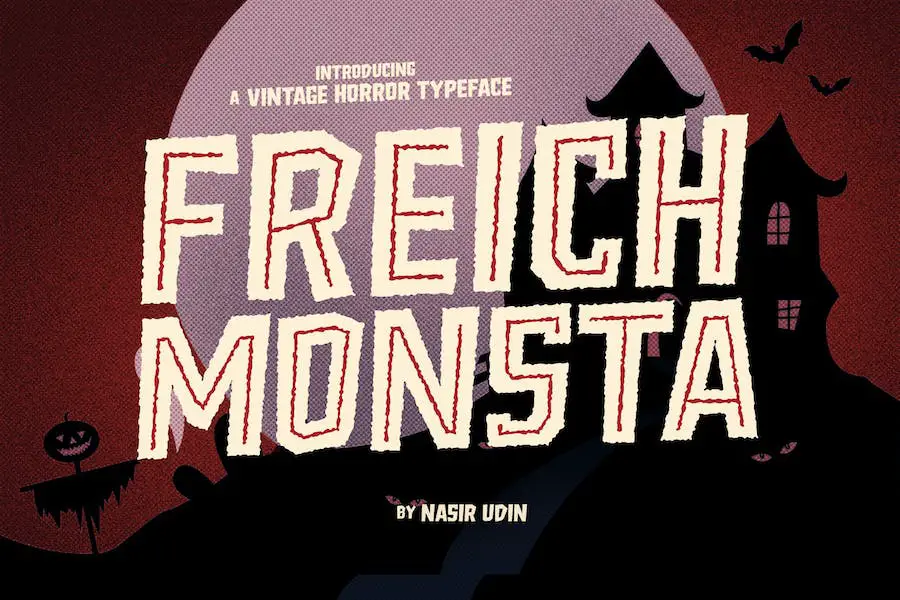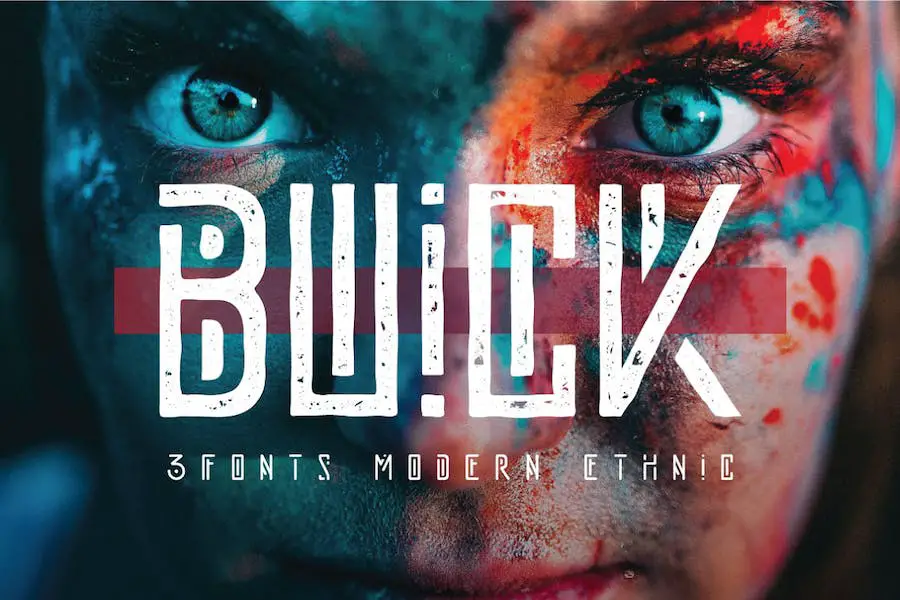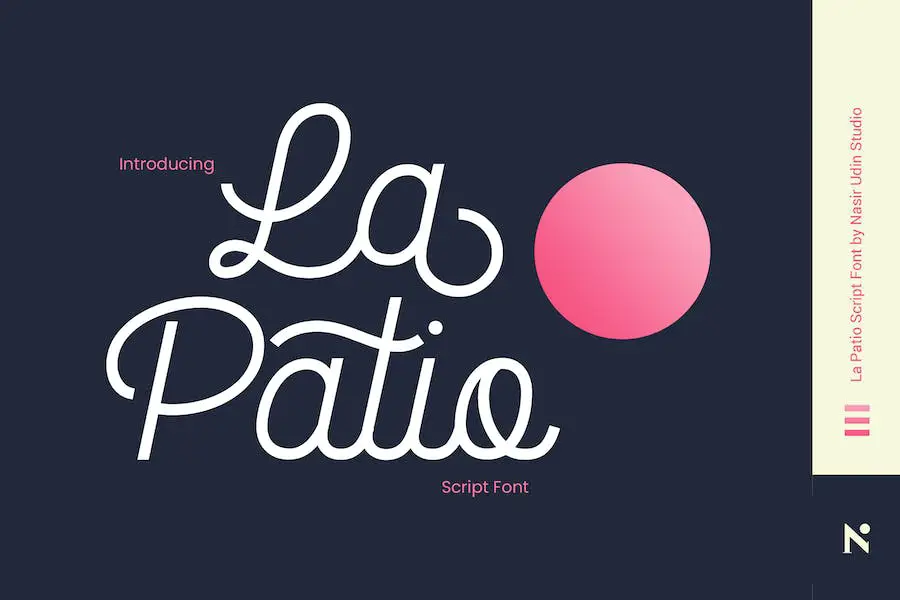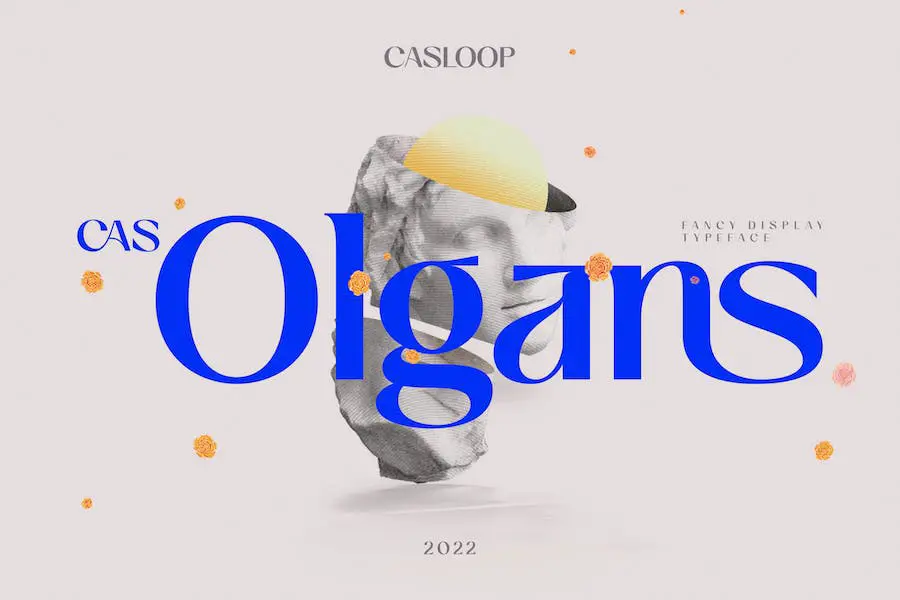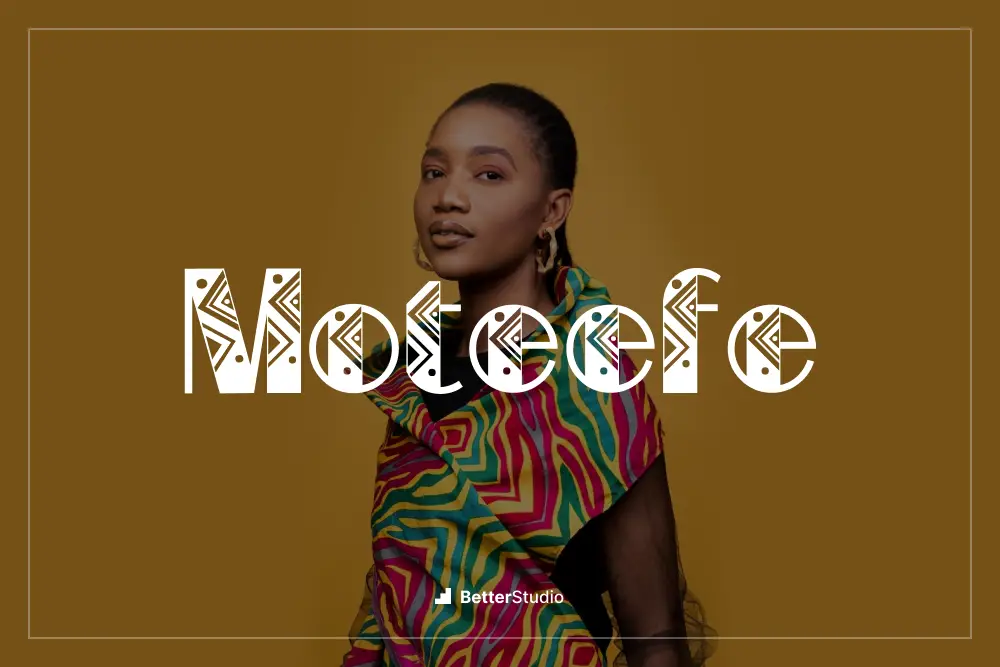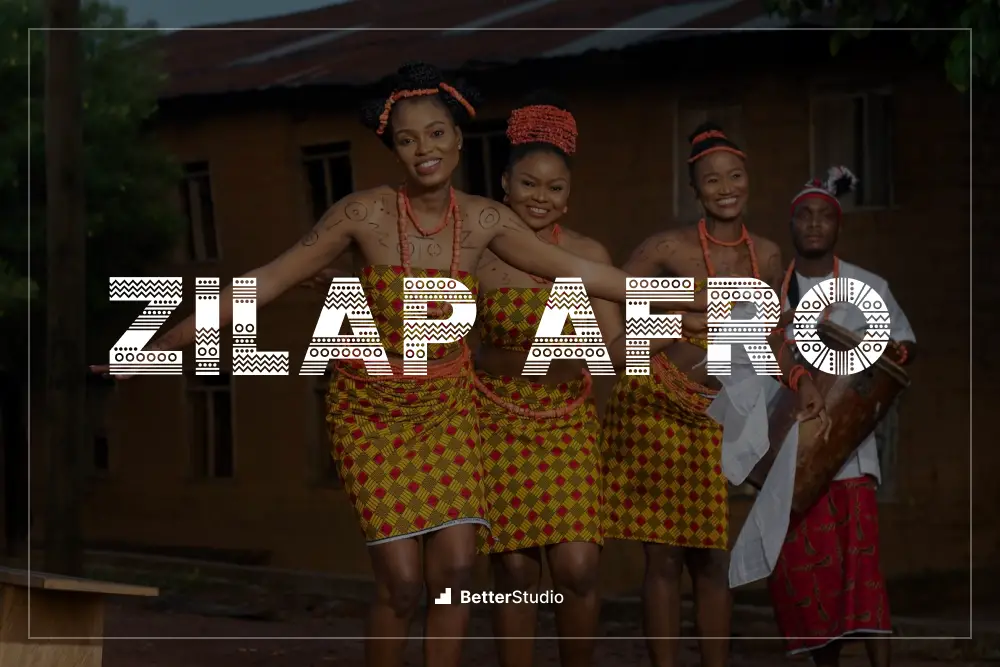
15 แบบอักษรแอฟริกันที่ดีที่สุด 2023 (ฟรีและพรีเมียม)
ในบล็อกโพสต์นี้ เราจะมาสำรวจแบบอักษรแอฟริกันที่ดีที่สุด 15 แบบที่จะนำสัมผัสแห่งวัฒนธรรมและความคิดสร้างสรรค์มาสู่การออกแบบของคุณอย่างแน่นอน แต่ก่อนที่เราจะเจาะลึก คุณอาจสงสัยว่าทำไมถึงใช้ฟอนต์แอฟริกัน?
แบบอักษรแอฟริกันนำเสนอสุนทรียศาสตร์ที่หลากหลายและหลากหลาย โดยได้รับแรงบันดาลใจจากวัฒนธรรมที่มีชีวิตชีวาของทวีป รูปแบบที่สลับซับซ้อน และสัญลักษณ์ตัวหนา แบบอักษรแต่ละแบบมีเรื่องราวของตัวเอง ช่วยให้คุณเพิ่มเอกลักษณ์เฉพาะตัวให้กับโครงการออกแบบของคุณได้
ตอนนี้เราได้ทำให้คุณสนใจแล้ว เรามาดูรายละเอียดสำคัญกันดีกว่า ในบทความนี้ เราจะนำเสนอแบบอักษรแอฟริกัน 15 อันดับแรกที่มีทั้งรูปลักษณ์โดดเด่นและใช้งานได้ดี
ตั้งแต่การประดิษฐ์ตัวอักษรที่หรูหราไปจนถึงการออกแบบที่ได้รับแรงบันดาลใจจากชนเผ่า แบบอักษรเหล่านี้ได้รับการคัดเลือกมาอย่างพิถีพิถันเพื่อให้เหมาะกับความต้องการในการออกแบบที่หลากหลาย ไม่ว่าคุณจะทำงานในโครงการสร้างแบรนด์ โปสเตอร์ หรือแม้แต่ส่วนหัวของบล็อก แบบอักษรเหล่านี้จะช่วยยกระดับงานของคุณและสร้างความโดดเด่นอย่างแน่นอน
ดังนั้น เพื่อไม่ให้เป็นการเสียเวลา กระโดดเข้าสู่โลกของแบบอักษรแอฟริกันและค้นพบอัญมณีที่ซ่อนอยู่ที่รออยู่ เตรียมพร้อมที่จะรับแรงบันดาลใจและปลดปล่อยความคิดสร้างสรรค์ของคุณในขณะที่เราสำรวจแบบอักษรแอฟริกันที่ดีที่สุด 15 แบบสำหรับนักออกแบบกราฟิก
คอยติดตามส่วนต่อๆ ไป ซึ่งเราจะเจาะลึกแต่ละฟอนต์ เน้นคุณลักษณะเฉพาะของฟอนต์ และยกตัวอย่างว่าสามารถนำมาใช้อย่างมีประสิทธิภาพในโครงการออกแบบต่างๆ ได้อย่างไร มาดำน้ำกันเถอะ!
แบบอักษรแอฟริกันระดับพรีเมียมที่ดีที่สุด
กำลังมองหาการเพิ่มกลิ่นอายแบบแอฟริกันให้กับงานออกแบบของคุณหรือไม่? การเลือกแบบอักษรแอฟริกันระดับพรีเมียมที่ดีที่สุดที่คัดสรรมาอย่างดีของเรา จะทำให้โครงการของคุณมีสุนทรียศาสตร์ที่มีเอกลักษณ์และเปี่ยมไปด้วยวัฒนธรรม อย่าพลาดแบบอักษรที่น่าดึงดูดเหล่านี้ ลองดูตอนนี้เพื่อรับประสบการณ์การออกแบบที่ไม่อาจลืมเลือน!
เซนเซโร โกรเตสค์
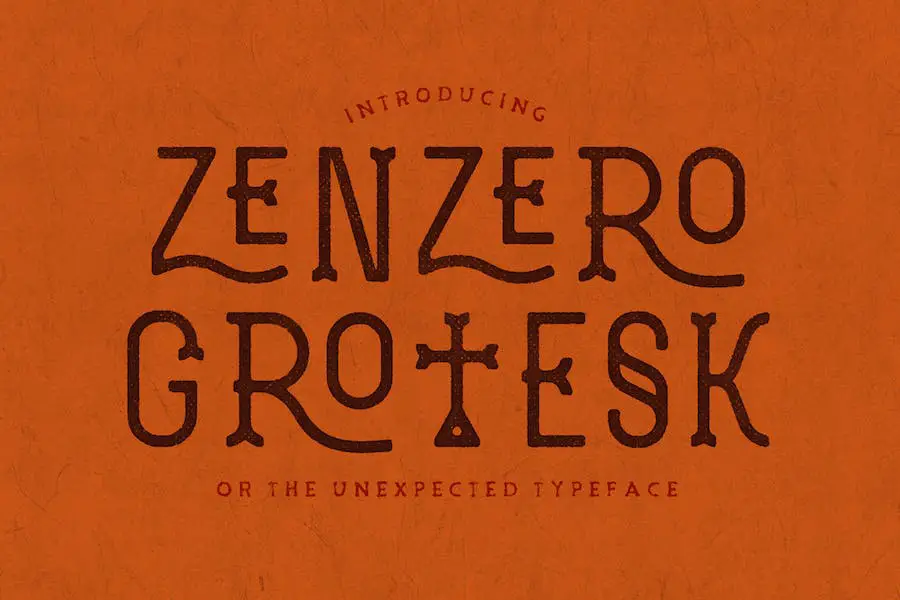
ขอแนะนำ Zenzero Grotesk แบบอักษรดิสเพลย์อเนกประสงค์และสะดุดตา ออกแบบโดย Valerio Dell'Edera แบบอักษรนี้ผสมผสานองค์ประกอบของทั้งแบบอักษร sans serif และแบบสแลบ ทำให้ได้รูปลักษณ์ที่สดใหม่และมีสไตล์
ด้วยคอลเลกชั่นอักษรควบและสัญลักษณ์ทางเลือกที่หลากหลาย Zenzero Grotesk นำเสนอความเป็นไปได้ไม่รู้จบสำหรับการสร้างสรรค์การออกแบบที่มีเอกลักษณ์และน่าดึงดูด
หนึ่งในคุณสมบัติที่โดดเด่นของ Zenzero Grotesk คือความสามารถในการปรับให้เข้ากับวัตถุประสงค์การออกแบบที่แตกต่างกัน ไม่ว่าคุณจะทำงานกับโลโก้ โปสเตอร์ หรือเว็บไซต์ แบบอักษรนี้สามารถยกระดับโปรเจ็กต์ของคุณและเพิ่มความแปลกใหม่ได้
ความเก่งกาจของมันทำให้คุณสามารถทดลองใช้เลย์เอาต์และความคิดสร้างสรรค์ที่หลากหลาย ทำให้คุณมีอิสระในการแสดงวิสัยทัศน์ที่เป็นเอกลักษณ์ของคุณ
ข้อได้เปรียบที่สำคัญของ Zenzero Grotesk คือมีอักษรควบและสัญลักษณ์สลับโวหารที่หลากหลาย องค์ประกอบเพิ่มเติมเหล่านี้ช่วยให้คุณควบคุมผลลัพธ์สุดท้ายได้อย่างสมบูรณ์ ช่วยให้คุณสามารถปรับแต่งแบบอักษรและสร้างตัวพิมพ์ที่โดดเด่นได้
ด้วยการใช้คุณสมบัติเหล่านี้ คุณสามารถเพิ่มความเก๋ไก๋และลักษณะเฉพาะให้กับข้อความของคุณ ทำให้ข้อความโดดเด่นและสร้างความประทับใจไม่รู้ลืม
วาโคลตู
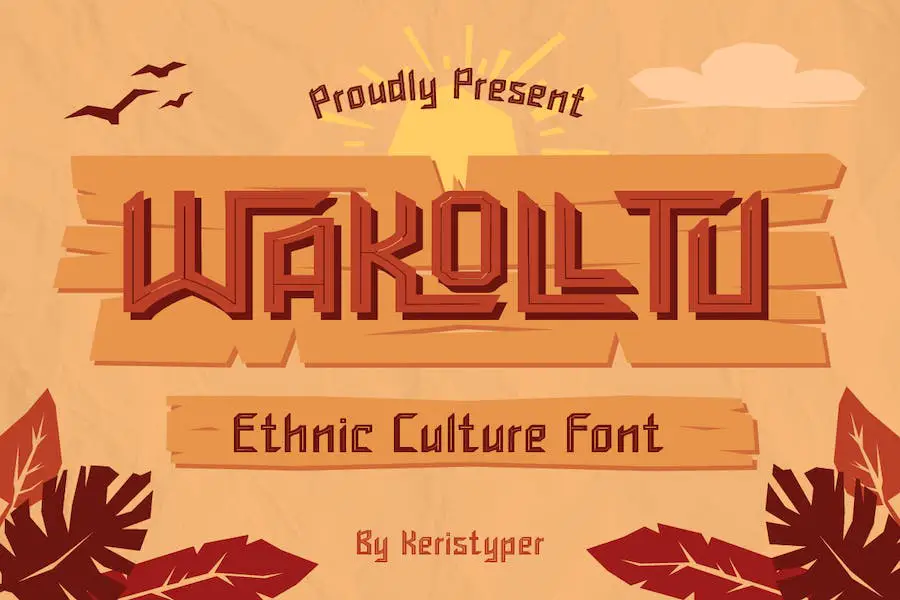
Wakolltu เป็นแบบอักษรวัฒนธรรมชาติพันธุ์ที่นำตัวละครที่สนุกสนานและมีชีวิตชีวามาสู่การออกแบบของคุณ เนื่องจากเป็นแบบอักษรดิสเพลย์จึงเหมาะสำหรับการใช้งานต่างๆ เช่น การออกแบบโลโก้ โพสต์บนโซเชียลมีเดีย ชื่อภาพยนตร์ ชื่อหนังสือ และแม้แต่ตัวอักษรข้อความสั้นหรือยาว
นอกจากนี้ยังทำงานได้ดีเป็นแบบอักษรข้อความรองเมื่อจับคู่กับแบบอักษร sans หรือ serif ด้วยสไตล์ที่เป็นเอกลักษณ์ Wakolltu เพิ่มสัมผัสของวัฒนธรรมแอฟริกันให้กับโปรเจ็กต์ของคุณ ทำให้พวกเขาโดดเด่นและดึงดูดผู้ชม
ไม่ว่าคุณจะเป็นนักออกแบบกราฟิกที่ต้องการปรับปรุงการออกแบบของคุณ หรือผู้ที่ต้องการเพิ่มสัมผัสที่แปลกใหม่และมีชีวิตชีวาให้กับการสร้างสรรค์ภาพของคุณ แบบอักษรนี้จะตอบสนองความต้องการของคุณอย่างแน่นอน ทำให้โปรเจ็กต์ของคุณมีรูปลักษณ์ที่แตกต่างและน่าดึงดูดใจด้วย Wakolltu หนึ่งในฟอนต์แอฟริกันที่ดีที่สุดที่มีอยู่
ฮาคูน่า
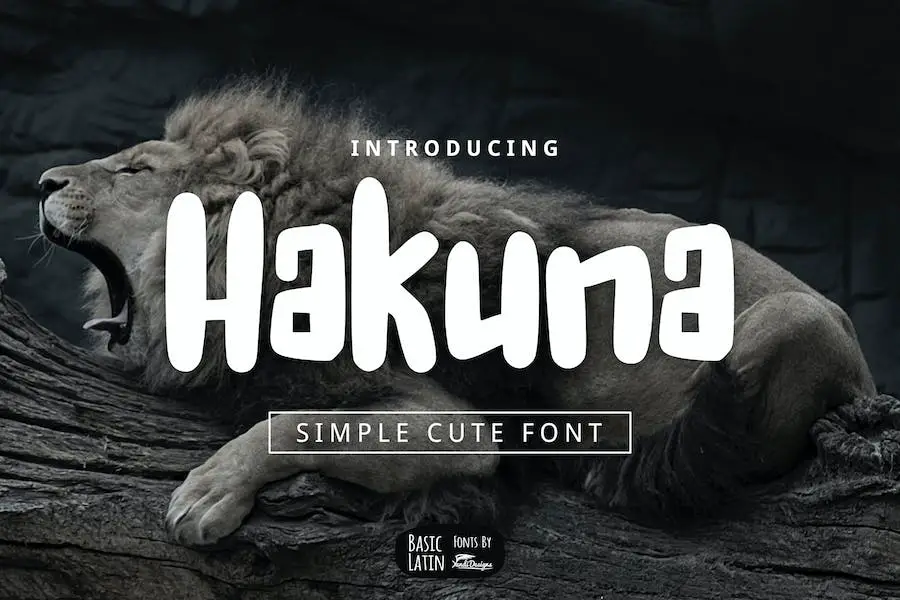
Hakuna เป็นฟอนต์พู่กันทำมืออเนกประสงค์ที่มีเสน่ห์ ซึ่งเพิ่มความเรียบง่ายและความน่ารักให้กับโปรเจ็กต์การออกแบบใดๆ ไม่ว่าคุณจะกำลังเขียนหนังสือสำหรับเด็ก สร้างคำพูดที่น่าดึงดูด หรือสร้างหัวเรื่องและชื่อเรื่องที่ดึงดูดความสนใจ แบบอักษรแอฟริกันนี้ก็คือสิ่งที่คุณต้องการ
ไม่ว่าคุณจะเป็นนักออกแบบกราฟิกที่สร้างงานออกแบบสำหรับ Canva หรือ Cricut Hakuna คือตัวเลือกที่สมบูรณ์แบบสำหรับการเพิ่มความเก๋ไก๋แบบแอฟริกันให้กับโปรเจ็กต์ของคุณ สไตล์พู่กันทำมือทำให้มันแตกต่างจากฟอนต์อื่นๆ ทำให้เป็นตัวเลือกที่โดดเด่นสำหรับผู้ที่มองหาสิ่งที่แตกต่าง
ความเรียบง่ายและความน่ารักของ Hakuna ทำให้ใช้งานง่ายมาก ความชัดเจนทำให้มั่นใจได้ว่าข้อความของคุณจะถูกส่งอย่างมีประสิทธิภาพ ในขณะที่จังหวะที่สนุกสนานช่วยเพิ่มความคิดสร้างสรรค์และความสนุกสนาน แบบอักษรนี้เหมาะสำหรับนักออกแบบที่ต้องการเพิ่มองค์ประกอบที่มีเอกลักษณ์และสนุกสนานให้กับโปรเจ็กต์ของตน
โทเท็มโบราณ
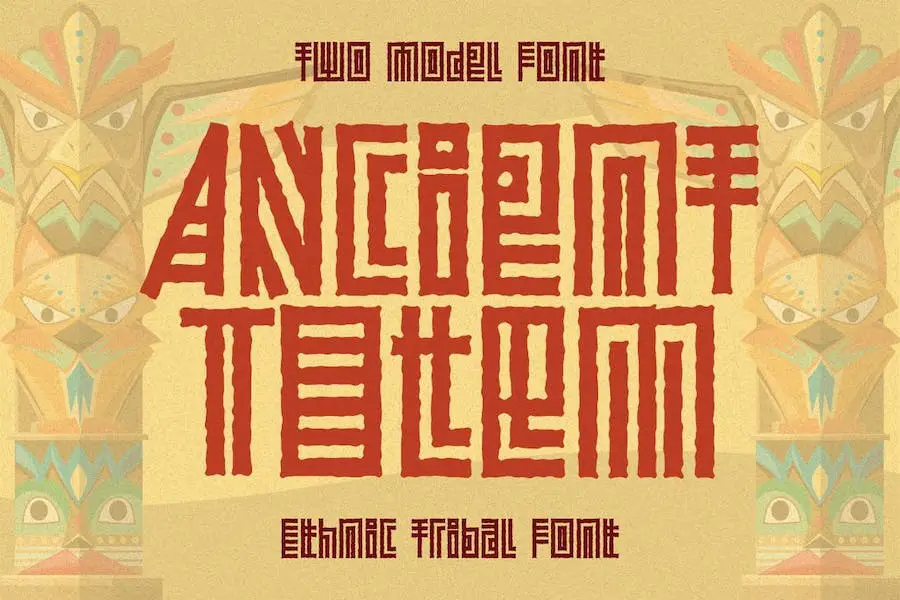
Ancient Totem เป็นแบบอักษรชนเผ่าชาติพันธุ์ที่นำเสนอแบบอักษรแบบจำลองที่แตกต่างกันสองแบบ ด้วยลักษณะเฉพาะที่สนุกสนานและมีเอกลักษณ์ จึงเหมาะอย่างยิ่งสำหรับการเพิ่มสัมผัสแห่งประเพณีและวัฒนธรรมให้กับโครงการออกแบบใดๆ
แบบอักษรที่แสดงนี้ได้รับแรงบันดาลใจจากสไตล์ชนเผ่าและจริยธรรมแบบดั้งเดิม ทำให้เป็นตัวเลือกที่ยอดเยี่ยมสำหรับนักออกแบบกราฟิกที่ต้องการปรับปรุงโปรเจ็กต์ของตนโดยมีกลิ่นอายของความเป็นของแท้